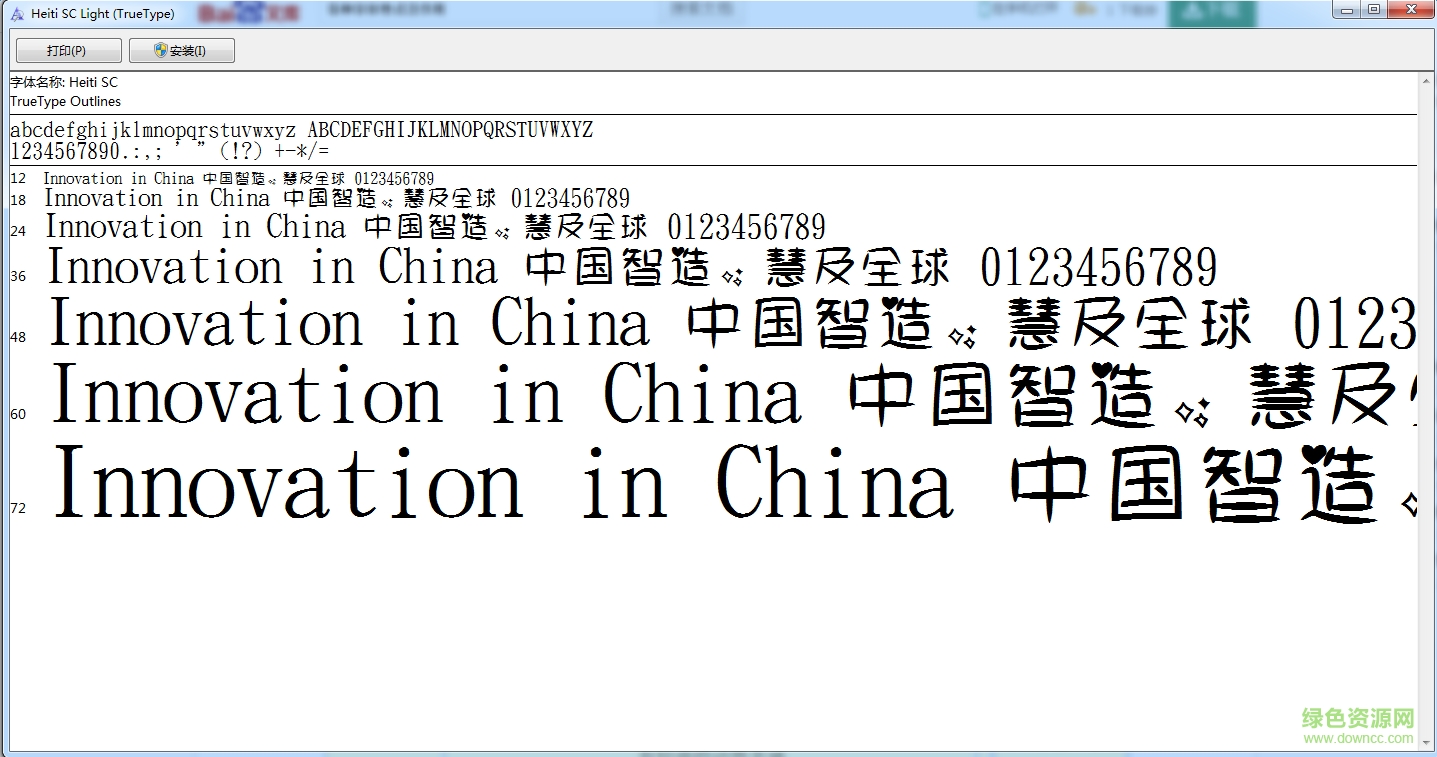
heiti sc light字體是一款英文襯線(xiàn)字體,字形秀美,構(gòu)思精巧,線(xiàn)條過(guò)渡自然,中文輸入帶有獨(dú)特的星光和小心心效果,十分漂亮,喜歡該字體的小伙伴歡迎在綠色資源網(wǎng)下載!
歷史學(xué)家們認(rèn)為襯線(xiàn)體來(lái)自于古羅馬的石刻碑文。對(duì)于這些裝飾性的筆畫(huà)為何會(huì)產(chǎn)生,起的何種作用,一直存在著爭(zhēng)議。大多數(shù)人所接受解釋來(lái)自 Edward Catich 神父,他在1968寫(xiě)了《The Origin of the Serif》一書(shū),認(rèn)為羅馬字母最初被雕刻到石碑上之前,要先用方頭筆刷寫(xiě)好樣子,雕刻的工匠之后照著寫(xiě)好的樣子雕鑿而成。由于直接用方頭筆刷書(shū)寫(xiě)會(huì)導(dǎo)致筆畫(huà)的起始和結(jié)尾出現(xiàn)毛糙,所以在筆畫(huà)開(kāi)始、結(jié)束和轉(zhuǎn)角的時(shí)候增加了收尾的筆畫(huà),也就自然形成了襯線(xiàn)。雕刻匠人照寫(xiě)好的字雕刻,就形成了所謂的“serif” 。